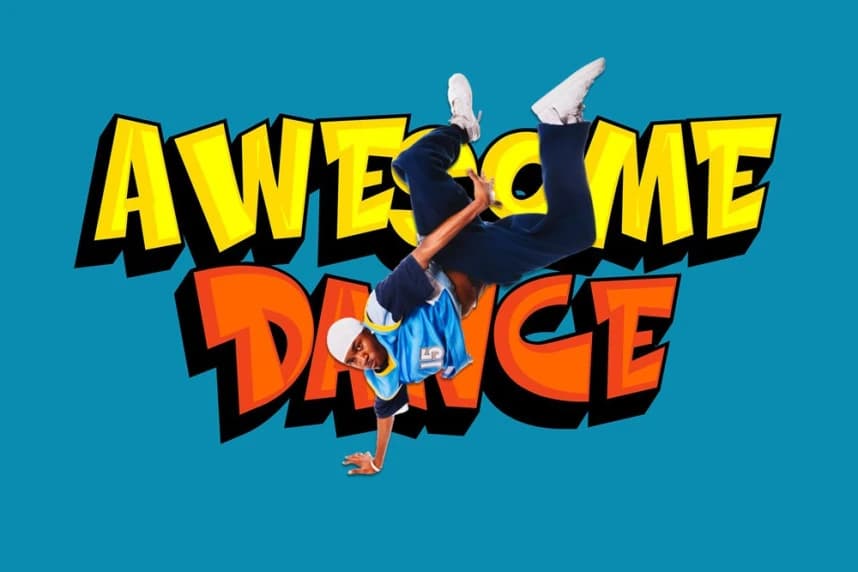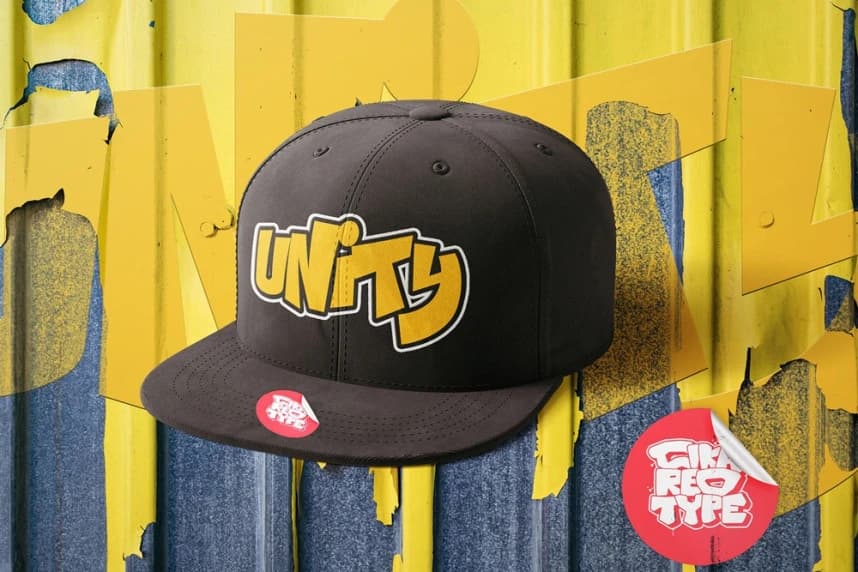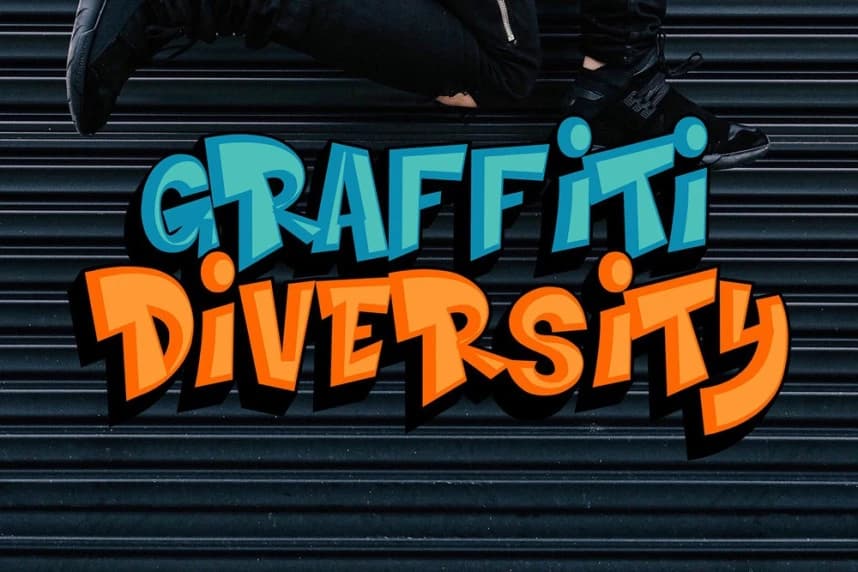
Hiper Hoper Font
Hiper Hoper Font, yeraltı sokak sanatından, boyutsal kentsel yazı karakterlerinden, hip hop kültüründen ve modern grafiti tipografisi trendlerinden esinlenen kalın 3D katmanlı bir grafiti yazı tipidir. Dinamik katmanlı efektlerle ve sokaklardan esinlenen ifade gücü yüksek karakter şekilleriyle tasar
Hiper Hoper Font, yeraltı sokak sanatından, boyutsal kentsel yazı stilinden, hip hop kültüründen ve modern grafiti tipografi trendlerinden ilham alan, kalın ve 3D katmanlı bir grafiti yazı tipidir. Dinamik katmanlı efektlerle ve sokak ilhamlı karakter şekillerinin ifade gücüyle tasarlanmıştır.